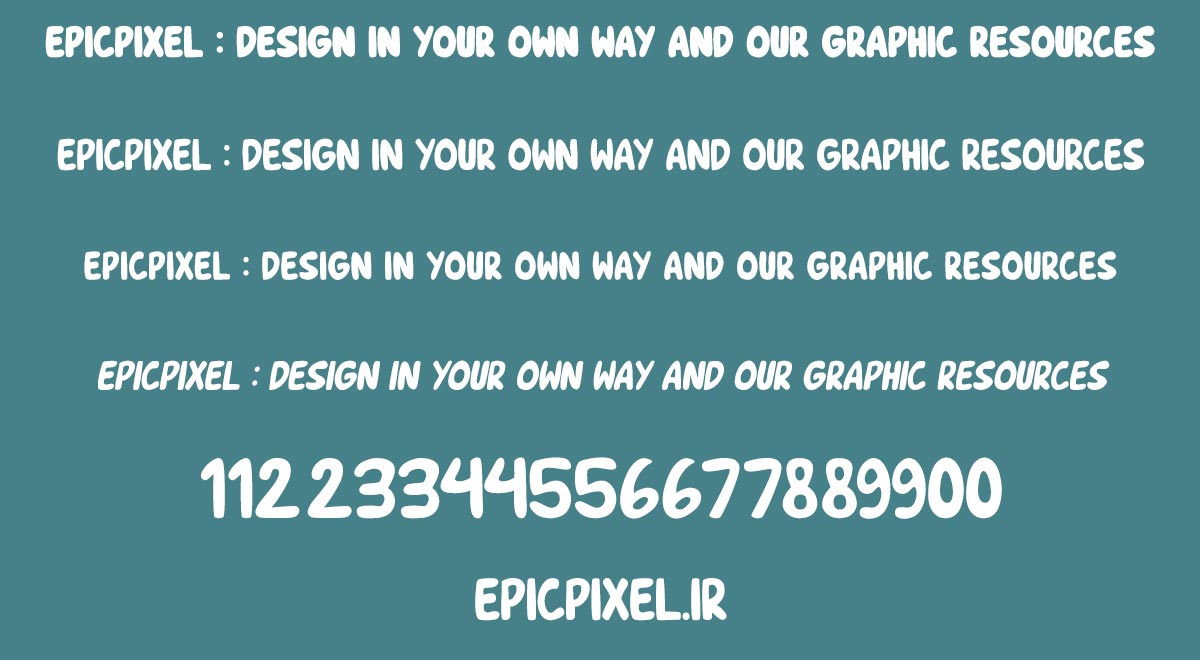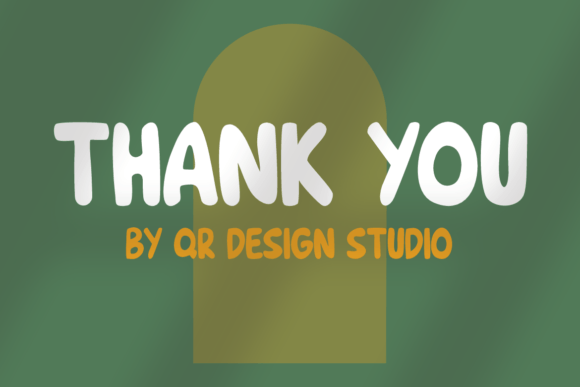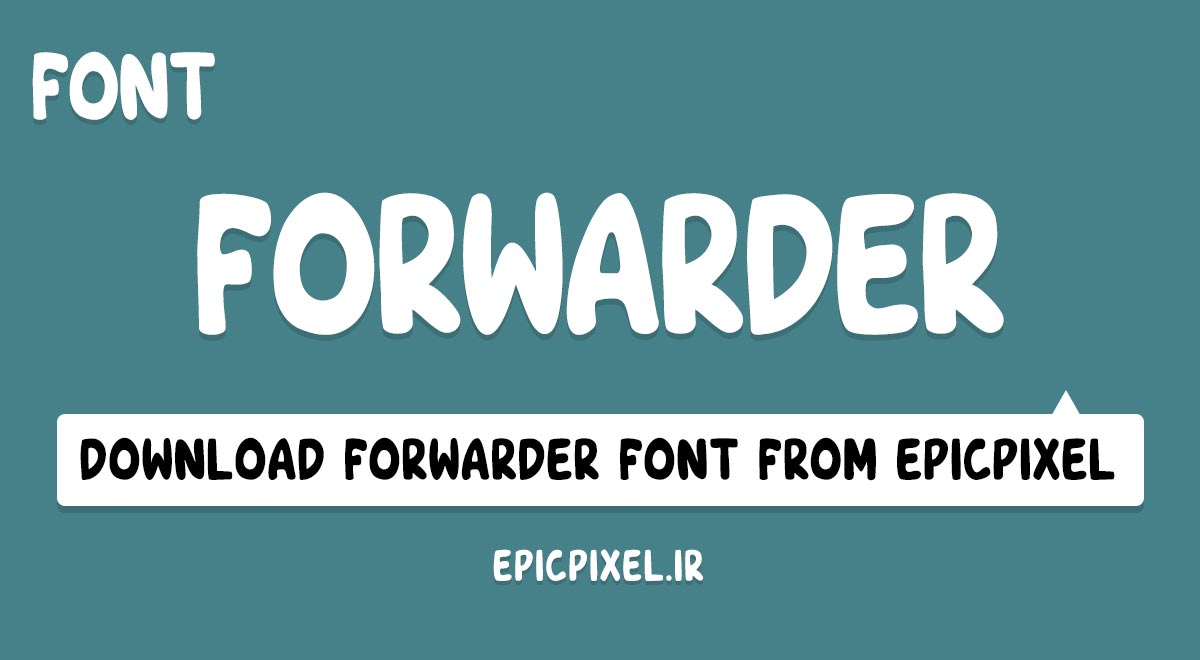
فونت Forwarder انگلیسی
دانلود فونت Forwarder انگلیسی Font فورواردر |
| ⭐ مجموعه فونت | دانلود فونت انگلیسی فورواردر Font Forwarder |
| ⭐ توضیحات | معرفی فورودر فونت، خطی پویا و رسا و حروف دستنویسی که انرژی و حرکت رو به جلو را تراوش میکند. این فونت با حروف روان و حروف پررنگ، جوهره پیشرفت و عزم را به تصویر می کشد.
فورودر فونت که برای نقل قولهای انگیزشی، مواد برندسازی و طرحهای معاصر ایدهآل است، حسی از هیجان و الهام را اضافه میکند و متن شما را با سبک پر جنب و جوش و جذاب خود به جلو میبرد. |